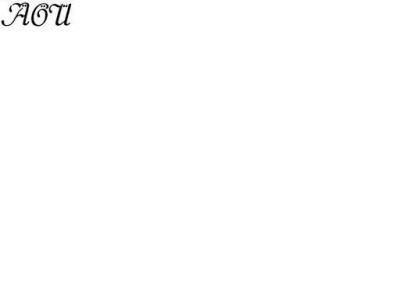
Schrift mit schönen Umlauten
bisher nur als stiller Leser, will ich nun mit einer konkreten Frage das Schweigen brechen:
Ich bin auf der Suche nach einer Schriftart, die schöne oder "pfiffige" Umlaute aufweist. Besonders wichtig wäre mir das "ä".
Primäre Anwendung ist eine Visitenkarte - entsprechend die Schriftgröße bei 8-10 pt. Der weibliche Vorname beginnt mit einem Ä gefolgt von einem n.
Bei meinen meisten bisherigen Entwürfen wirkt das "Ä" als Anfangsbuchstabe entweder viel zu flau und nach oben verzogen oder aber unter der Wucht der beiden Punkte zerdrückt und gepresst. Meine Antwort darauf war eine feine gleichmäßige Grotesk mit runden Punkten. Doch besonders bei der Position der Punkte will mir bisher keine Version richtig gefallen. Am ehesten gefällt vielleicht noch eine dünne Avenir.
Habt ihr Erfahrung mit Umlauten am Wortanfang?
Könnt ihr mir eine Schriftart empfehlen?
Auf welche besonderen Kriterien muss ich achten?
Was haltet ihr von einem kleinen "ä", das auf Großbuchstaben-Versalhöhe vergößert werden könnte :D ?
Umlaute sind oft nicht ideal gelöst – insbesondre (was verständlich ist) oft, wen die Schriftgestalter nicht aus einem Sprachraum kommen, wo so etwas täglich gebraucht wird. Grundsätzlich muss das »vergrößerte« ä nicht schlecht aussehen, aber es ist heikel, man findet da sicherich mehr gescheiterte als gelungene Versuche, wenn man sich auf die Suche begibt. Insbesondre müsstest Du darauf achten, das die Strichstärke sich harnonisch einpasst oder Du musst Sie anpassen, was u.U. einigen Aufwand macht und auch dann nicht immer zu befriedigenden Ergebnissen führt.
Aber: wenn es bei der Visitenkarte um eine einmalige Gestaltung geht, ist es ein gangbarer Weg, Dir Umlaute nach Deinem Geschmack selbst zu machen. Das ist nicht so schwer. Beachten solltest Du bei runden Pünktchen, dass oft eine leichte Abweichung vom perfekten Kreis optisch harmonischer ist.
Gibt es denn Schriftgestalter, die aus entsprechenden Sprachräumen kommen und somit besonderen Wert speziell auf die Umlaute legen/gelegt haben?
Den Tipp zur Kreisform werde ich beherzigen und entsprechend ausprobieren.
Als wäre das mit dem Ä nicht genug, sind Vor- und Nachname außerordentlich kurz. Grade die filigranen Fonts verdampfen sich mir da sehr gerne auf den Entwürfen... werde da wohl vor allem mit Laufweite und sanften Grautönen arbeiten um auch mächtigere Schnitte noch anzupassen.
Gibt es denn Schriftgestalter, die aus entsprechenden Sprachräumen kommen und somit besonderen Wert speziell auf die Umlaute legen/gelegt haben?
Adam Twardoch und Filip Blažek legen da zum Beispiel sehr viel Wert darauf.
Die Ä-Punkte findest du konkret hier:
Also ich weiß nicht...
Es gibt soviele wunderschöne Lösungen für Versal-Umlaute.
Und dazu noch mehr Beispiele bei den Schreibschriften, wo es u.a. auch Alternativen des Versal-Ä gibt, die dem Gemeinen a entsprechen von der Form her.
Ich kann das Problem nicht erkennen.
"Selbermachen". Joh... sicher. Lucian Bernhard würde sich wohl im Grab umdrehen, wenn Ihr versuchen würdet, sein Umlaut-Punkte des Versal-Ä zu "korrigieren" :D
Aber schon gut... soll kein Angriff sein.
Schnitzt Ihr Euch ruhig Eure Schriften zurecht.
"Selbermachen". Joh... sicher. [schriftgestalter XY] würde sich wohl im Grab umdrehen, wenn Ihr versuchen würdet, sein Umlaut-Punkte des Versal-Ä zu "korrigieren" :D
Wenn [schriftgestalter XY] gestümpert hat, weil er sich mit dem konkreten Problemfall nicht ausgekannt hat, darf man ihn korrigieren.
"Selbermachen". Joh... sicher. [schriftgestalter XY] würde sich wohl im Grab umdrehen, wenn Ihr versuchen würdet, sein Umlaut-Punkte des Versal-Ä zu "korrigieren" :D
Wenn [schriftgestalter XY] gestümpert hat, weil er sich mit dem konkreten Problemfall nicht ausgekannt hat, darf man ihn korrigieren.
Selbstverständlich.
Wobei - wozu sollte man eine Schrift von einem Stümper einsetzen?
@bleisetzer: Bei deinen Beispielbildern werden alle Punkte neben dem A angeordnet. Grade das fande ich persönlich bisher nicht sonderlich gut.
"Also ich weiß nicht... Es gibt soviele wunderschöne Lösungen für
Versal-Umlaute."
Auch wenn den bitteren Unterton überlese, bleibt mir bisher die Wunderschönheit des Äs verborgen. Aber vielleicht kannst du mich eines besseren belehren. :)
Die ersten Versuche die Punkte selbst anzugehen, sind kläglich gescheitert. Bin mir nicht sicher ob ich damit zu einem zufriedenstellenden Ergebnis kommen werde :(
Noch etwas, druck Deine Favoriten zwischendurch auch mal in der richtigen Größe aus, das wirkt oft anders als auf dem Bildschirm.
PS.:Mein Favorit wäre die Futura, wo die Pukte einen wunderbaren Kontrast zum A bilden, allerdings ist hier die x-Höhe recht gering
Hatte nun vier Entwürfe gemacht. Verwendet wurde einmal Avenir, einmal die Futura, als Kontrasporgramm die Palatino und auf wunsch die Lucida Sans.
Die Avenir ist es schließlich geworden. :)